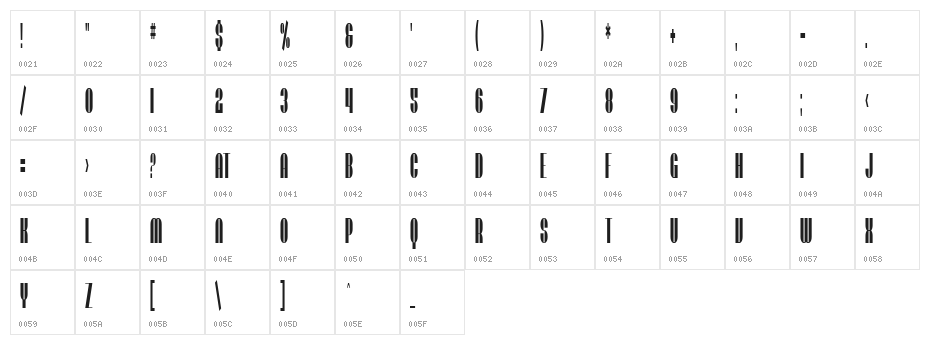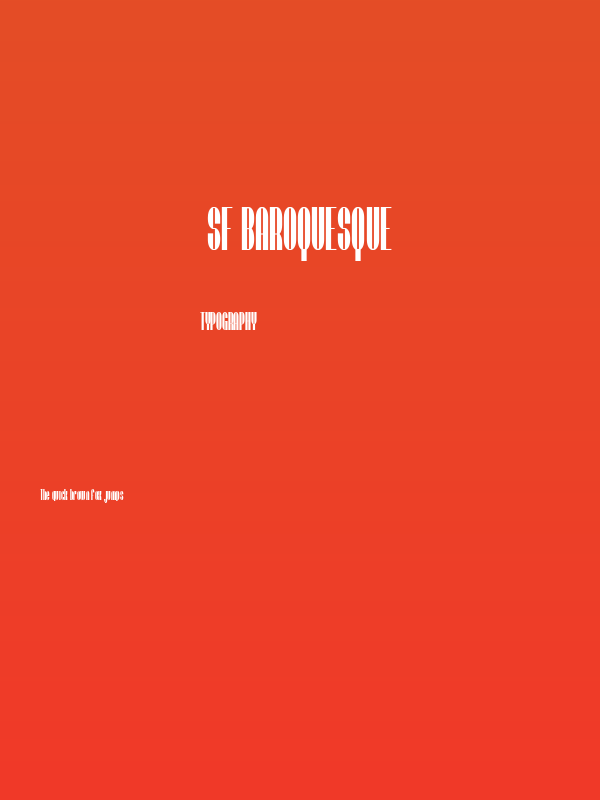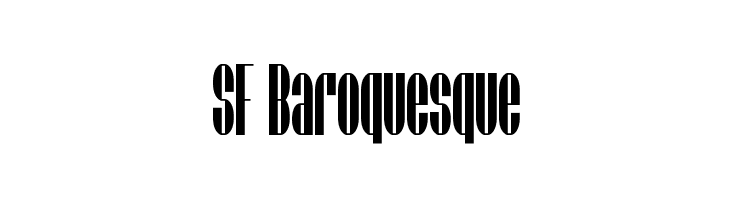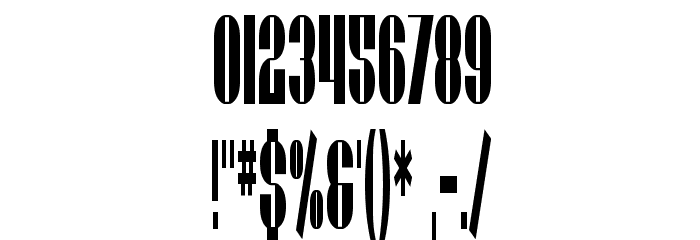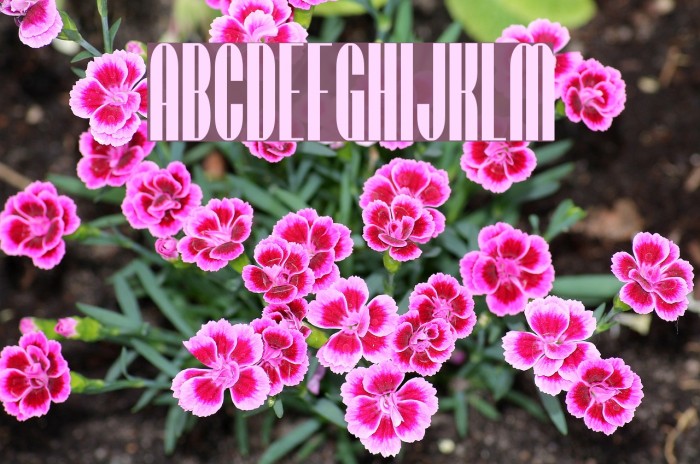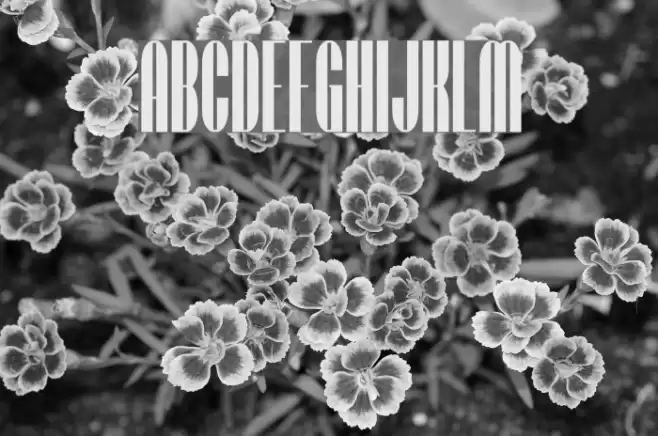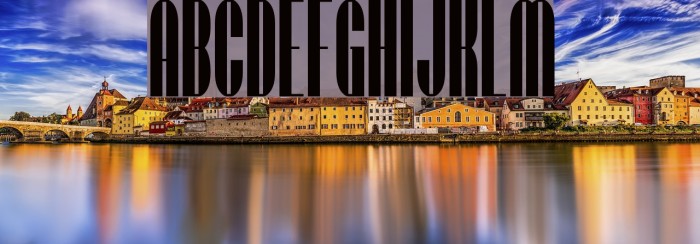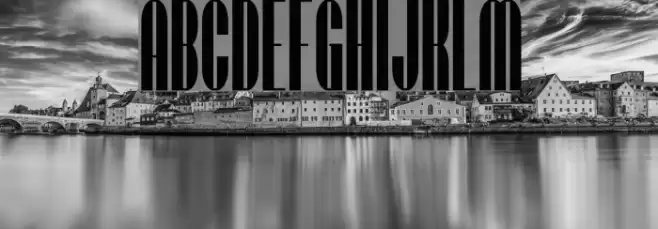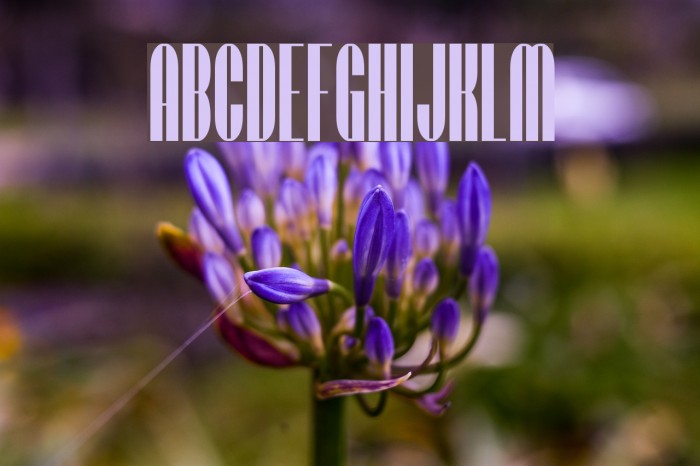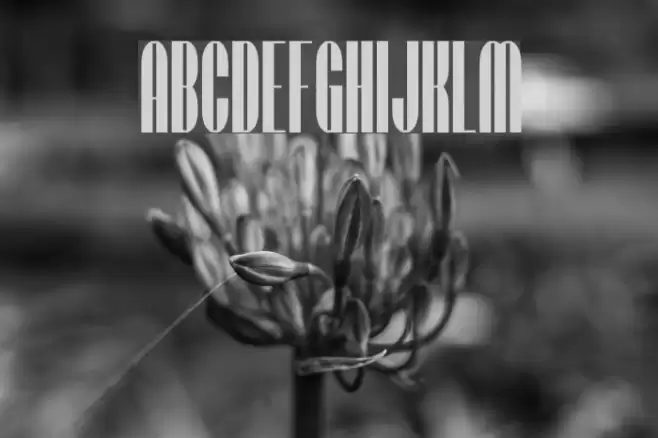
SF Baroquesque Font
| Vorgeschlagene Projekte | Ideal for headlines, posters, branding, and any project requiring a striking and elegant display font. |